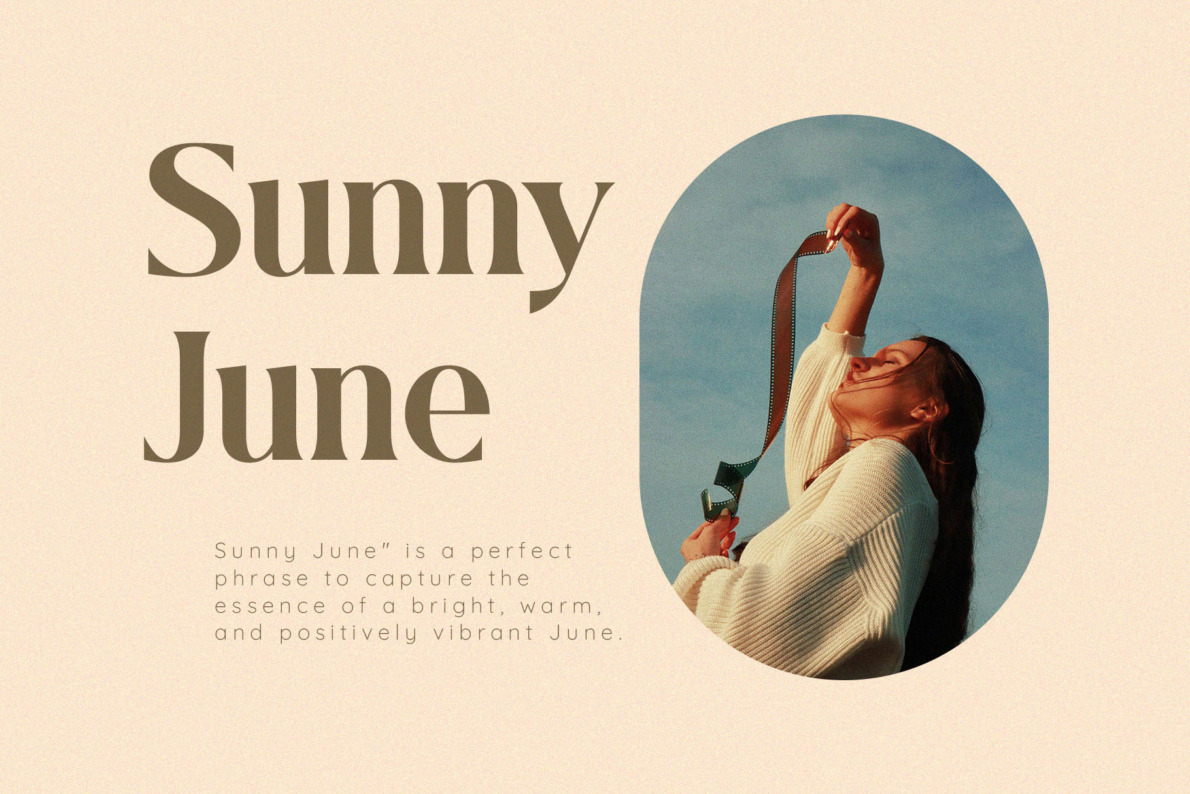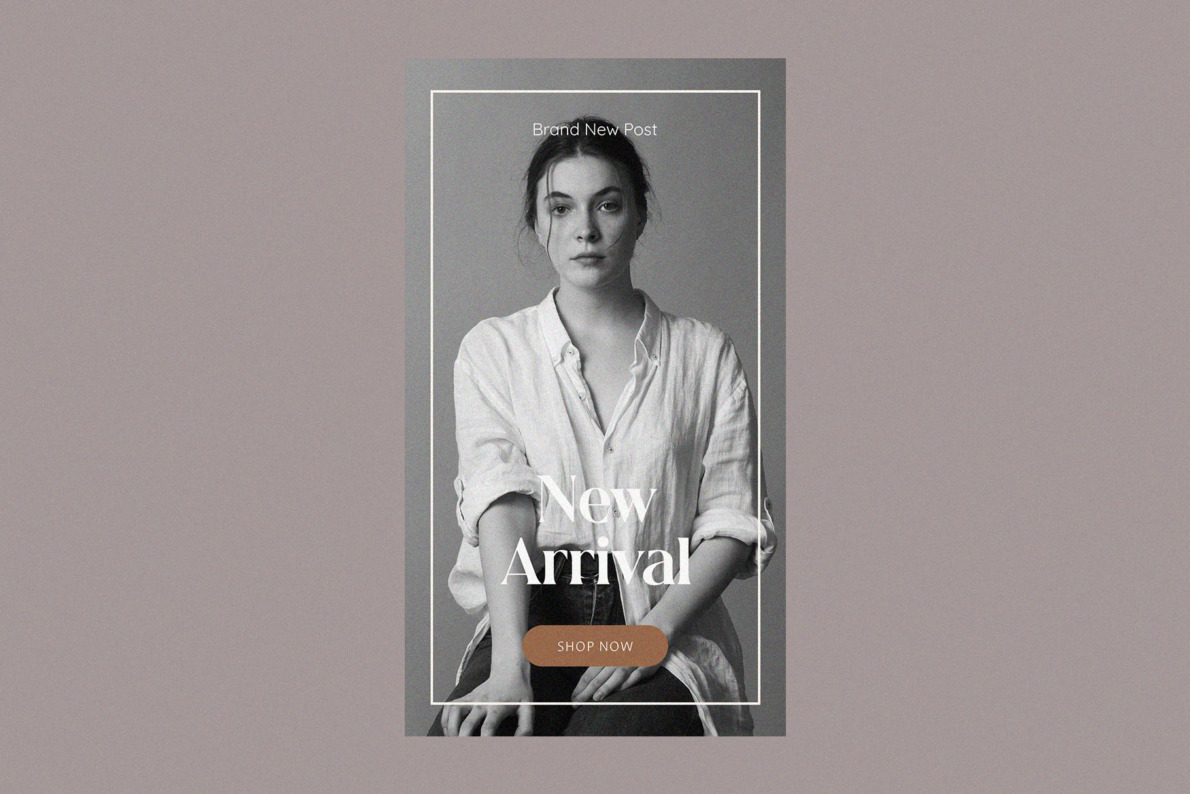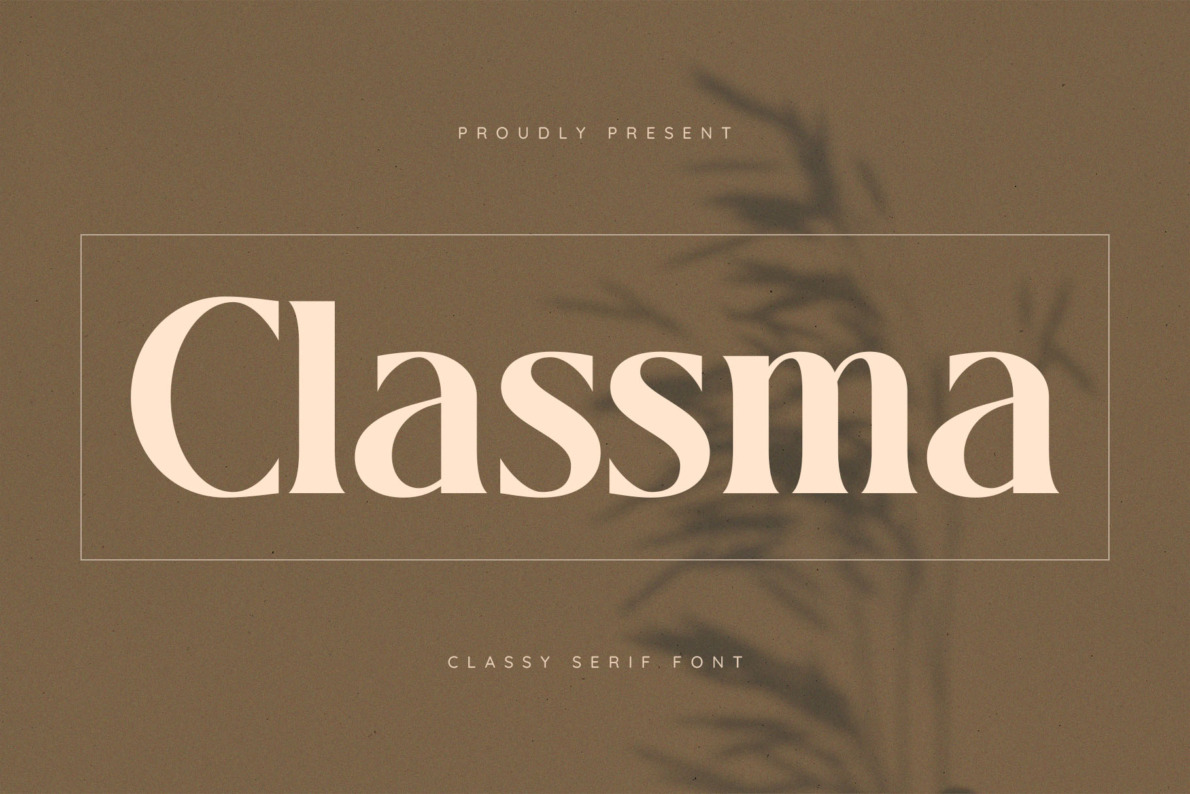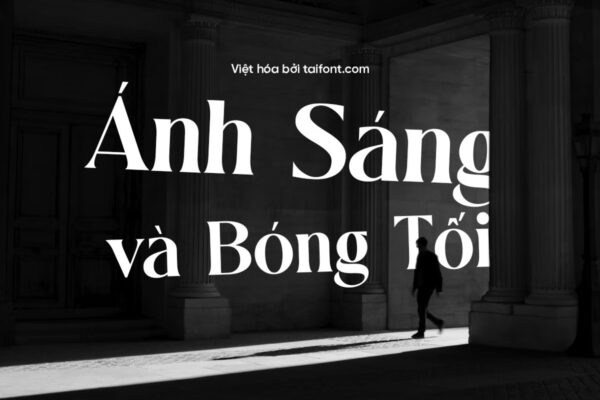
Giới thiệu về Font TF Classma Việt hóa
TF Classma Việt hóa là một font chữ có chân (serif) nổi bật với thiết kế nét nhẹ nhàng, thanh lịch nhưng vẫn đầy sức hút. Font này mang đến vẻ đẹp cổ điển pha lẫn hiện đại, toát lên phong thái tinh tế và sang trọng, lý tưởng để tạo điểm nhấn duyên dáng và thu hút mọi ánh nhìn.
Với đặc điểm là nét chữ thanh thoát, tính thẩm mỹ cao và phong thái trang nhã, Classma là lựa chọn lý tưởng cho các thiết kế muốn truyền tải sự tinh tế và đẳng cấp:
- Thiết kế thời trang: Hoàn hảo cho các thương hiệu thời trang cao cấp, từ logo, nhãn mác sản phẩm, lookbook, đến các chiến dịch quảng bá bộ sưu tập. Font này giúp truyền tải vẻ đẹp thanh lịch, đẳng cấp và độc đáo của trang phục, nâng tầm giá trị thương hiệu.
- Thiết kế tạp chí: Lý tưởng để sử dụng cho các tiêu đề chính, lời dẫn, hoặc nội dung bài viết trong các tạp chí về thời trang, nghệ thuật, kiến trúc, hoặc lối sống. Nét chữ có chân của Classma giúp tăng tính trang trọng và dễ đọc, đồng thời tạo cảm giác cao cấp, thu hút độc giả.
- Tiêu đề: Tuyệt vời để tạo các tiêu đề phụ, chú thích hoặc các dòng chữ ngắn cần sự tinh tế trên poster, banner, hoặc các ấn phẩm truyền thông. Font này mang lại sự cân bằng hoàn hảo giữa tính dễ đọc và tính thẩm mỹ cao.
Với TF Classma Việt hóa, bạn có thể dễ dàng thổi hồn tinh tế, sang trọng và vẻ đẹp hoàn hảo vào các thiết kế, tạo ra những sản phẩm không chỉ đẹp mắt mà còn đầy cảm xúc và sức hút đặc biệt.